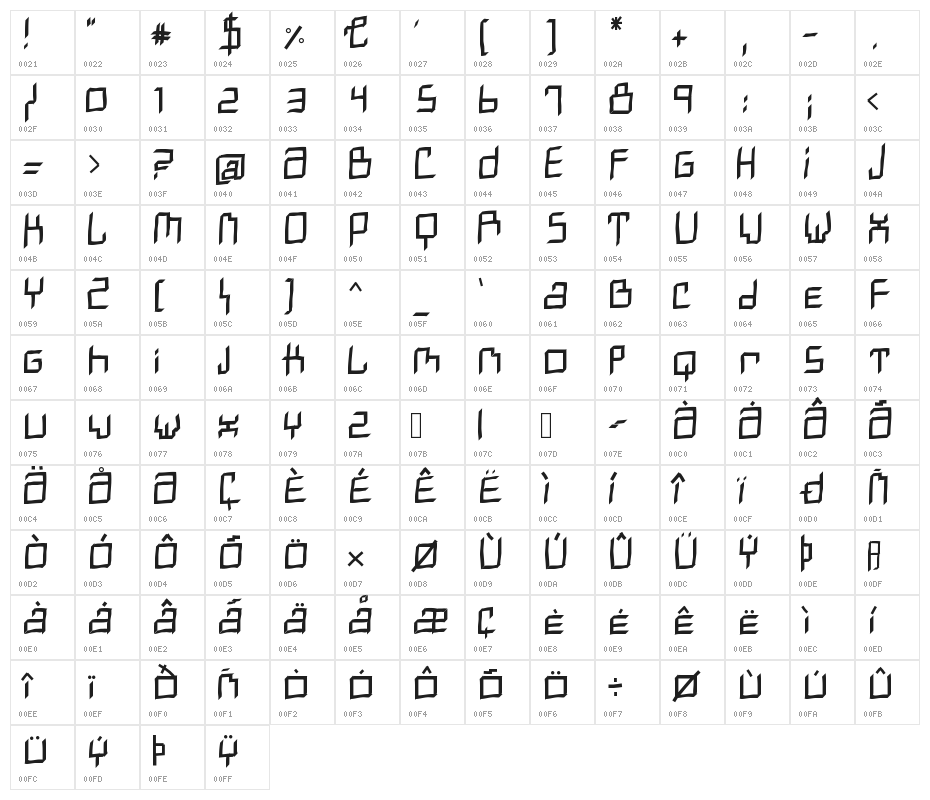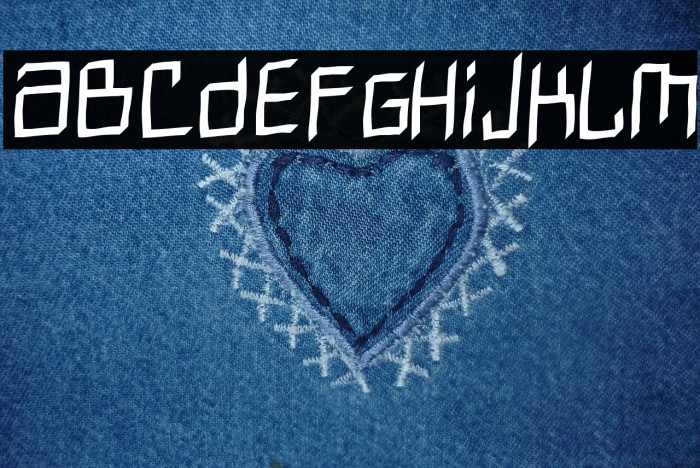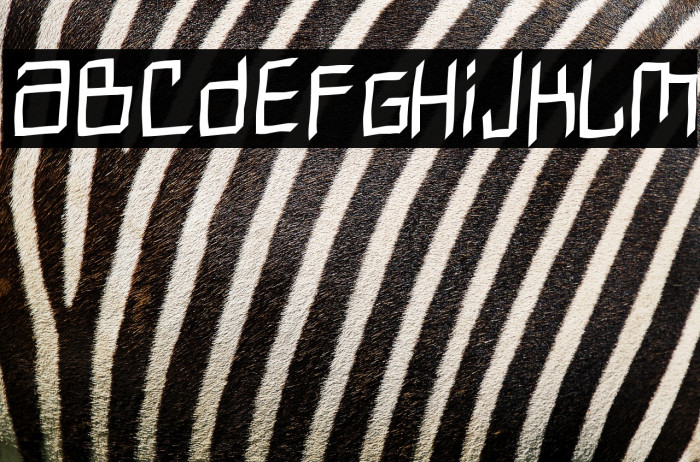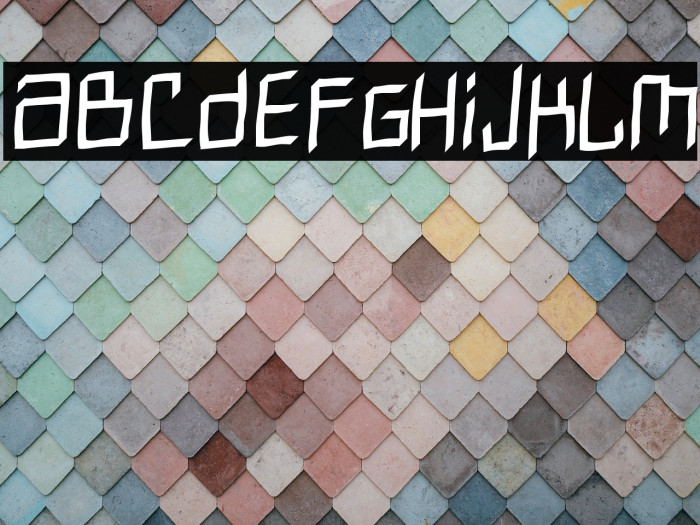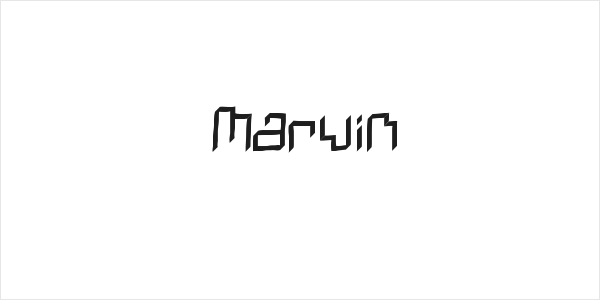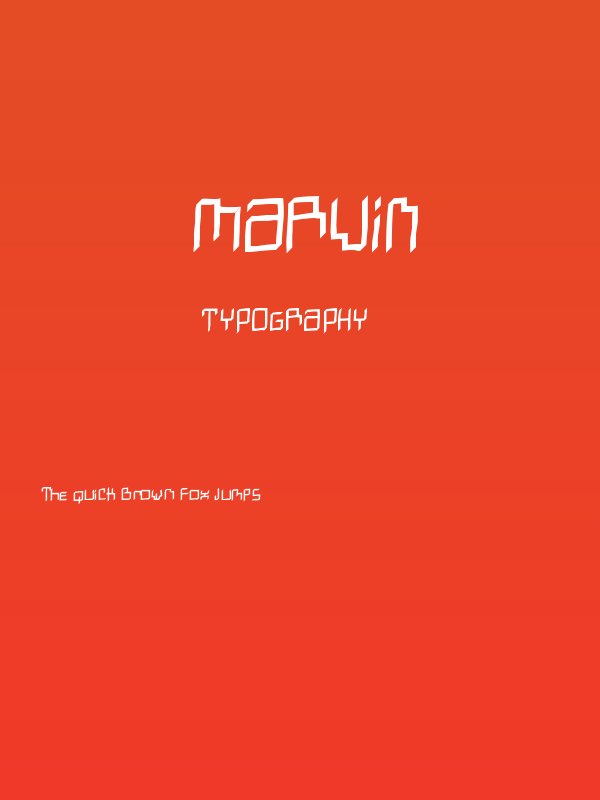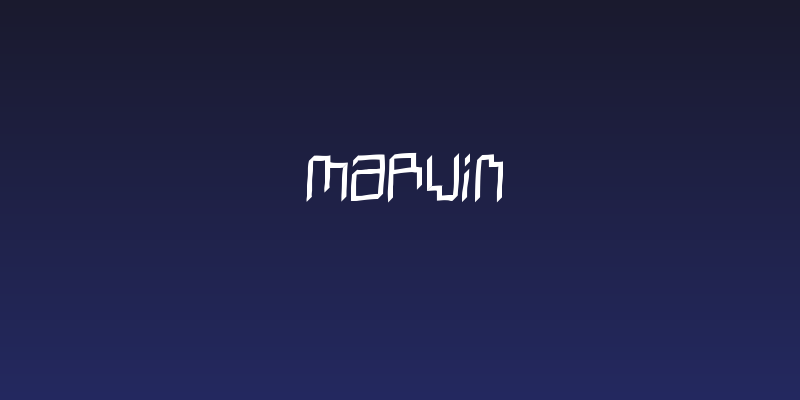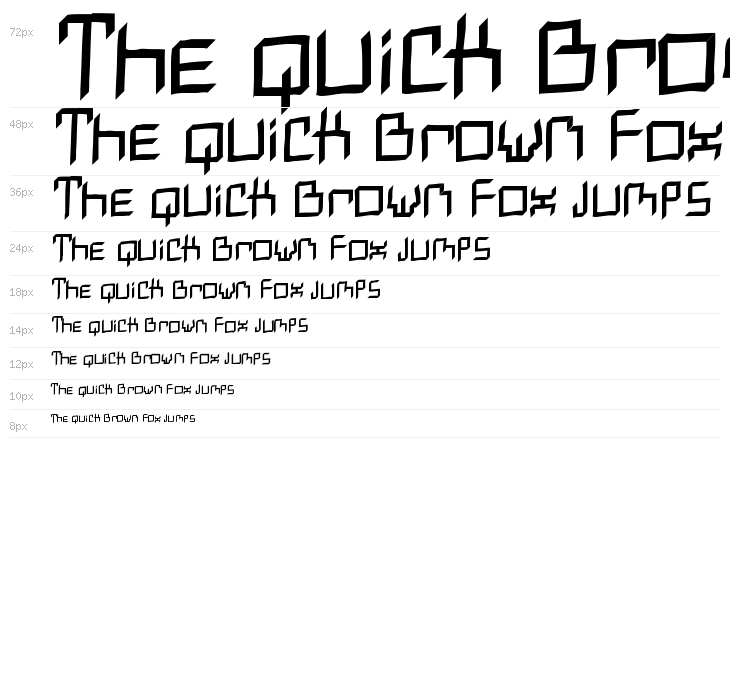
Marvin Font
| حالة الاستخدام | Logos, Headlines, Posters |
| مشاريع مقترحة | Ideal for sci-fi themed projects, modern branding, video game titles, and edgy poster designs. |